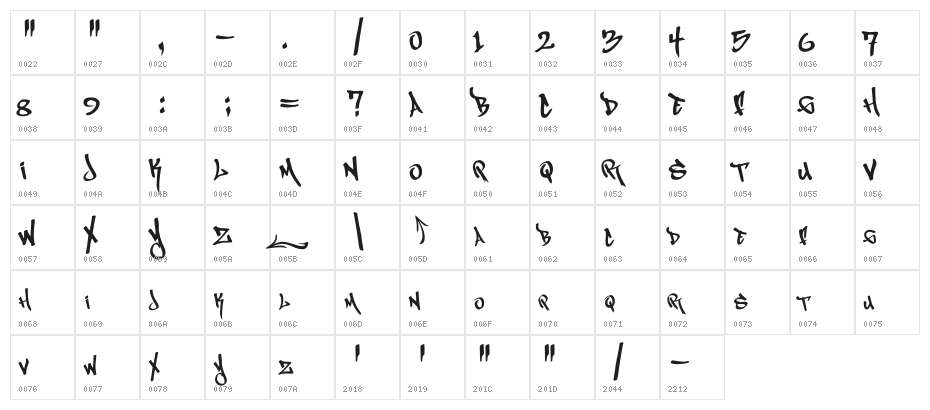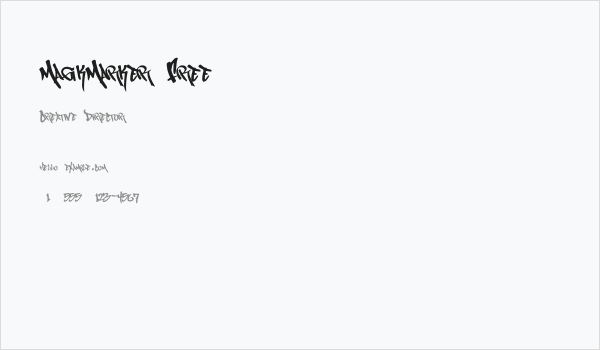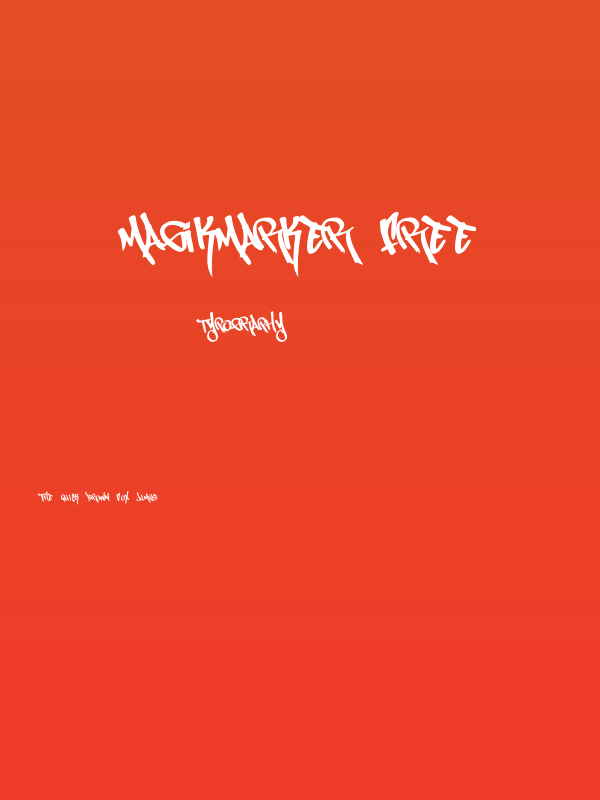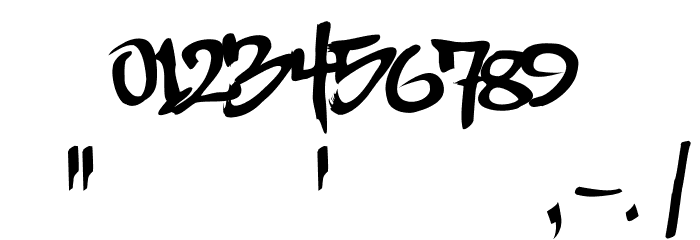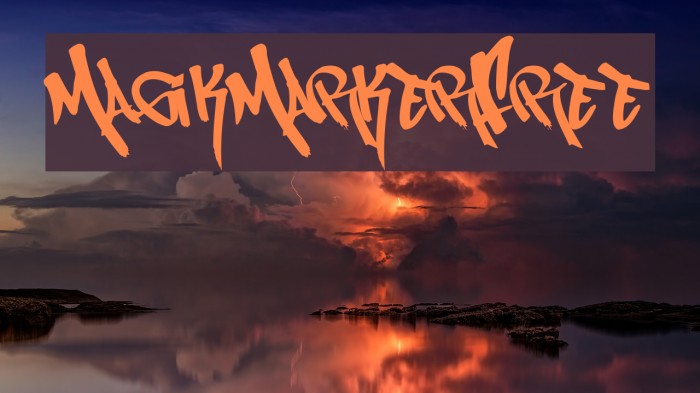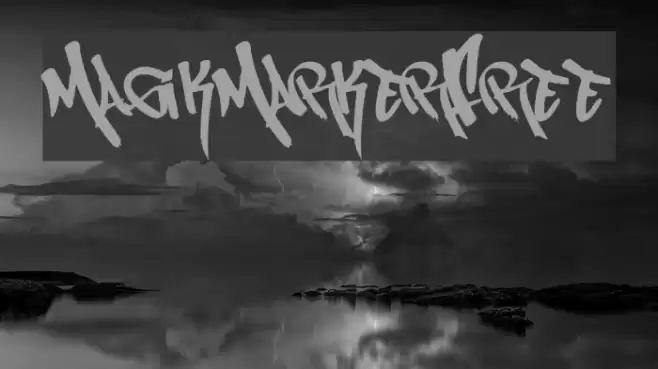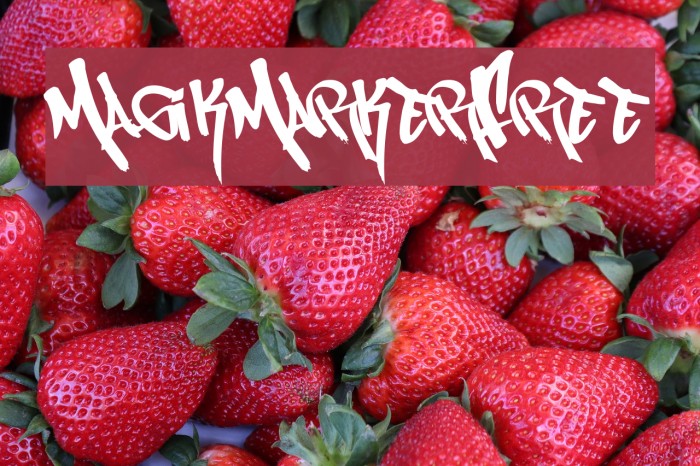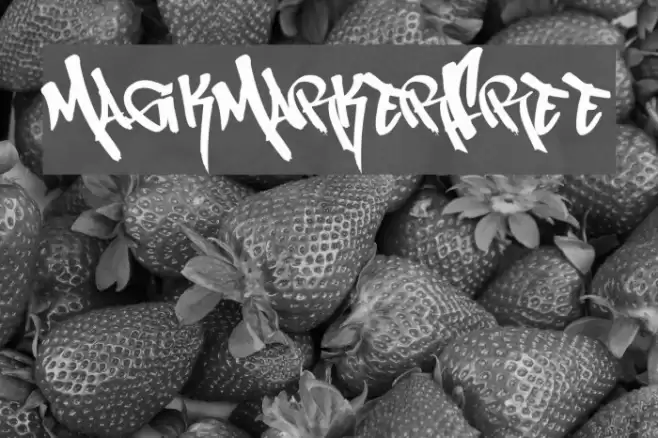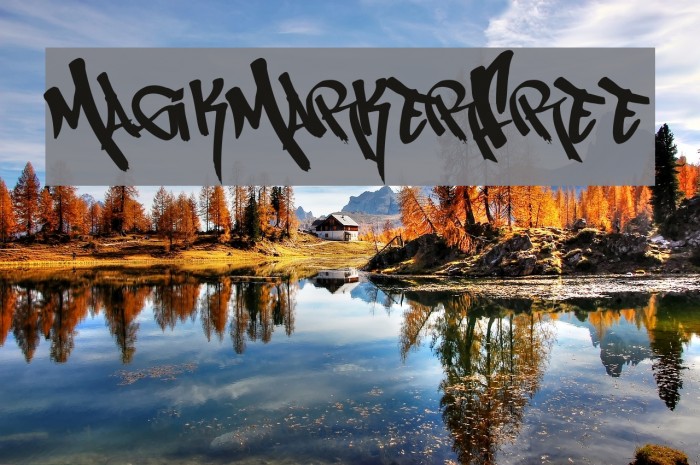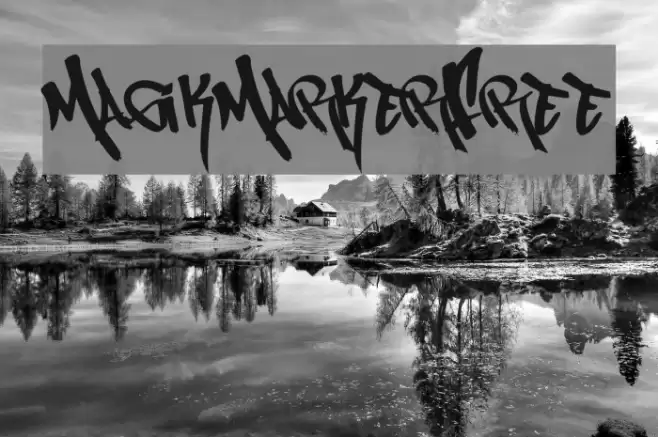
MagikMarker_Free Font
| श्रेणियाँ | Graffiti |
| कंट्रास्ट | High |
| समग्र शैली | Modern, Urban |
| उपयोग का मामला | Headlines, Logos, Posters |
| सुझाए गए प्रोजेक्ट | Ideal for street art designs, urban-themed posters, music album covers, and edgy branding projects. |